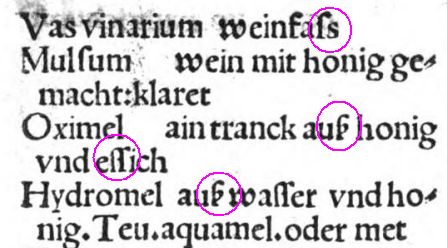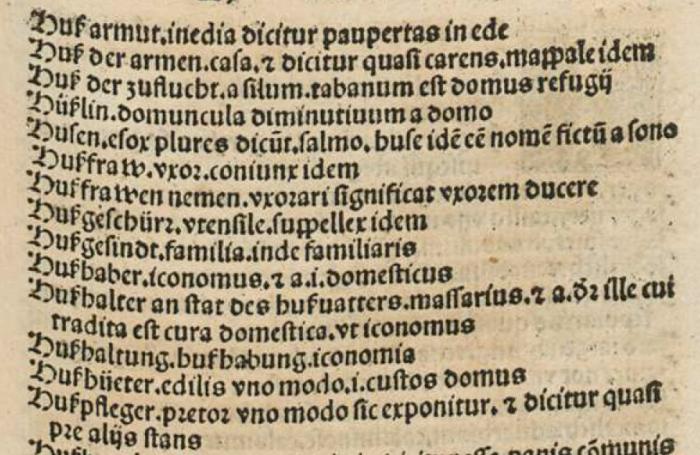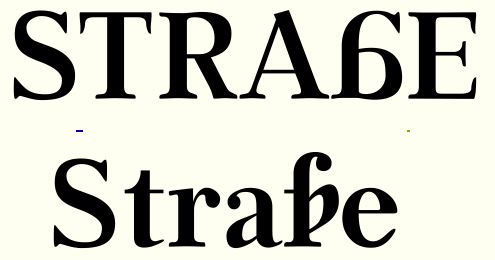
Und wieder das lange s.
Hallo! Mir kommt in letzter Zeit öfter dieses lange s unter, das ein Ornament zu haben scheint. Hat es irgendeine Funktion, oder ist es nur eine Ziervariante? Und, zweite Frage, hat es einen Namen?
Beispiel 1. Vocabularius: primo ponens dictiones theutonicas, Straßburg 1515:
Beispiel 2. Ex Promptuario uocabulorum Iohannis Piniciani uariarum rerum uocabula, 1522:
Beispiel 3. Nochmal dasselbe Buch wie Beispiel 2:
So man die Textstellen, die ich mit violetten Kringeln gekennzeichnet habe, begutachtet, mag man zu dem Eindruck gelangen, es handele sich um eine Schreib- und Schmuckvariante von “ſs”. Andrerseits wäre es  ungewöhnlich, daß auch das Wort “aus” und “Haus” mit einer Variante von “ſs” geschrieben wurde. Was meint ihr?
Das ist laut Max Bollwage ein langes s mit einer Art diakritischem Zeichen, das aus dem stimmhaften ein stimmloses s machen sollte – quasi der Vorgänger des ß. Bollwage geht davon aus, dass dieser Bogen fälschlicherweise als z interpretiert wurde und so der Name Eszett entstanden ist.
Wäre man bei dieser Form geblieben, hätte man sicherlich weniger Probleme mit der Verwechselung mit B oder β, sondern auch noch eine gute Chance auf einen ebenso weniger verwechselbaren Großbuchstaben gehabt.
Kann es sein, daß dieses Ornament und Zeichen der Abbreviatur ist und ein Doppel-s abbreviert, ähnlich wie man es auch vom q her kennt, das mit einem verticalen “Schwuppdiwupp” die Endung -que abbrevierte? Soweit ich das sehe kommt es nur in deutschem Text vor, selbst wenn in einem Buch der deutsche Text mit derselben Antiqua gedruckt wurde wie der lateinische Text. D. h. es muß etwas sein, was im Lateinischen nicht gesetzt werden durfte, denke ich.
Kann es sein, daß dieses Ornament ein Zeichen der Abbreviatur ist, so wie man es vom q her kennt, das mit einem verticalen “Schwuppdiwupp” die Endung -que abbrevierte? Und es damit einfach doppel-s abbreviert.
Wohl eher nicht, sonst hätte man es evtl. konsequenter eingesetzt.
Das ist laut Max Bollwage ein langes s mit einer Art diakritischem Zeichen, das aus dem stimmhaften ein stimmloses s machen sollte – quasi der Vorgänger des ß
@Schnitzel Ist Bollwage eine Autorität? Was mich an dem Argument stört, ist, daß ich bezweifle, daß man sich im 15. / 16. Jd. über stimmloses s Gedanken machte. Zu dieser Zeit war Phonetik nicht Thema, sondern eher Zierstriche, wie z. B. auch das “j”, was zu der Zeit damals nichts anderes als ein geschwungenes “i” war, mit einem “Swash”. Ich habe versucht etwas bei MUFI zu finden. Aber bis auf ein Zeichen genannt LATIN SMALL LETTER LONG S WITH FLOURISH, das ein wenig anders aussieht, evtl. aber passen könnte, steht dort auch nichts.
Flourish = Verzierung?
Hmmm ...
Irgendwie scheint diese Variante dann zu stehen, wenn der nachfolgende Buchstabe nicht unter's lange s schlüpfen kann, weil Oberlänge, bzw. keine passende Ligatur da ist bzw. ein Leerzeichen folgt ... Evtl. also doch einfach nur lückenfüllender Zierrat? Warum es alternativ langes und rundes s am Ende gab ... *schulterzuck*
PS: So unähnlich finde ich das MUFI-Symbol gar nicht ...
Ich persönlich empfinde es als reichlich anmaßend, den Leuten damals eine ordentliche Ortografie abzusprechen, und solche Zeichen schlicht als Zierrat abzutun, der ohne Sinn einfach nach Gutdünken gesetzt wird. Wäre das der Fall, würde das auch sicherlich deutlich mehr aus optischen Gründen gemacht.
Nein, wenn ich mir Texte aus dioeser Zeit ansehe, erkenne ich durchaus eine durchdachte, und in sich schlüssige ortografische Logik, die nur ebmen nicht mehr die unsere ist.
So sehe ich in dem Zeichen auch aus dem Einsatz in den Beispielen recht deutlich eine der Frühformen des ß.
Dieser Buchstabe war ja praktisch damals in gleicher Findungsphase, wie heute sein großer Kollege ẞ, den wir alle ja ebenso in den unterschiedlichsten grafischen Varianten gesehen haben.
Irgendwie scheint diese Variante dann zu stehen, wenn der nachfolgende Buchstabe nicht unter's lange s schlüpfen kann, weil Oberlänge, bzw. keine passende Ligatur da ist bzw. ein Leerzeichen folgt ...
Hallo Mueck, interessante Überlegung. Allerdings paßt bei “Huſarmut" das a durchaus unter das lange s.
@catfonts Von unsinnig und Gutdünken war nicht die Rede. Genauso wie es feste Regeln wann langes s, wann r rotunda, wann j statt i gesetzt wurde, gab es womöglich auch eine Regel für das lang s mit Zierat, auch wenn wir sie nicht erkennen. Aber nochmal: mit Buchstaben phonetische Varianten zu unterscheiden war zu dieser Zeit kaum ein Thema.
Nochmal zurück zu den Textstellen. Dort steht nebeneinander, bei demselben Autor “weinfaſs” und “weinfaſ(+Zierrat)”. D. h. hier könnte der Autor zwei verschiedene Schreibungen haben, eine mit einem s, die andere mit zwei s. So ein Nebeneinander von verschiedenen Schreibungen bei demselben Autor zu der damaligen Zeit waren nicht unüblich. Dennoch vermute ich, daß es nur zwei Druckformen für dieselbe Schreibung war, d. h. beidesmale weinfass mit zwei s. Was meint ihr?
Aber letztlich sind wir dank der etwas verunglückten Reform ja auch wieder zu einer etwas freieren Schriftsprache zurückgekehrt, und es haben sich, gerade bei Verlagen durchaus interne Varianten, als Zwischenlösung aus alter und neuer Rechtschreibung entwickelt, was natürlich auch dieses Schwarz-Weiß-Denken aus Richtig und Falsch etwas aufzuweichen ermöglicht. Richtig krude Schreibweisen bleiben dann auch falsch, aber etwas mehr Freiheit schadet bestimmt nicht.